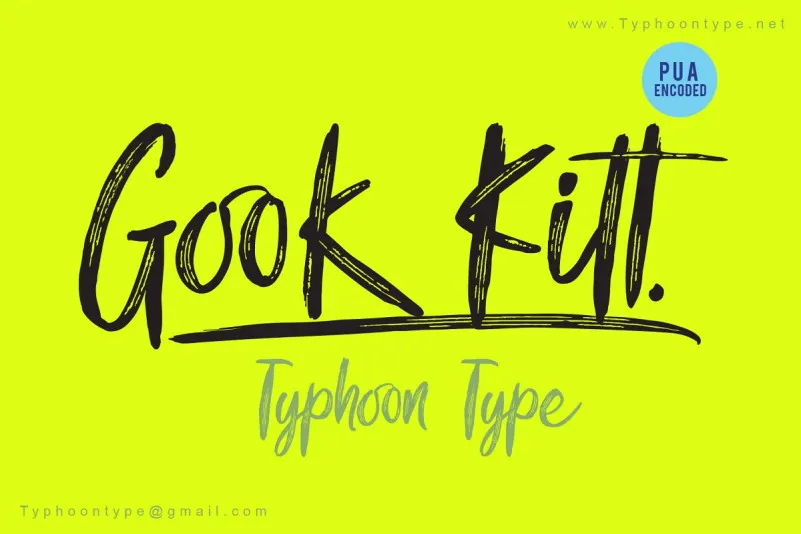
Descubra a modernidade sofisticada do Gook Kitt Brush Font! Esta elegante fórmula tipográfica apresenta traços suaves e fluidos que são perfeitos para criar uma identidade visual única, seja para sua marca na logomarca ou em adesivos de nome. Suas linhas arredondadas e sua consistência macia fazem deste um fonte ideal para as embalagens de produtos, roupas customizadas, materiais promocionais e até mesmo como uma forma criativa de personalizar cartões de agradecimento ou mensagens nas redes sociais. Engaje seu público com essa fórmula tipográfica moderna que incorpora um toque de handbrush para torná-la ainda mais autêntica e versátil. Nossa fonte Gook Kitt é uma escolha perfeita para todos os projetos digitais onde você deseja incluir um touch de personalidade. Descubra o seu próprio Gook Kitt!